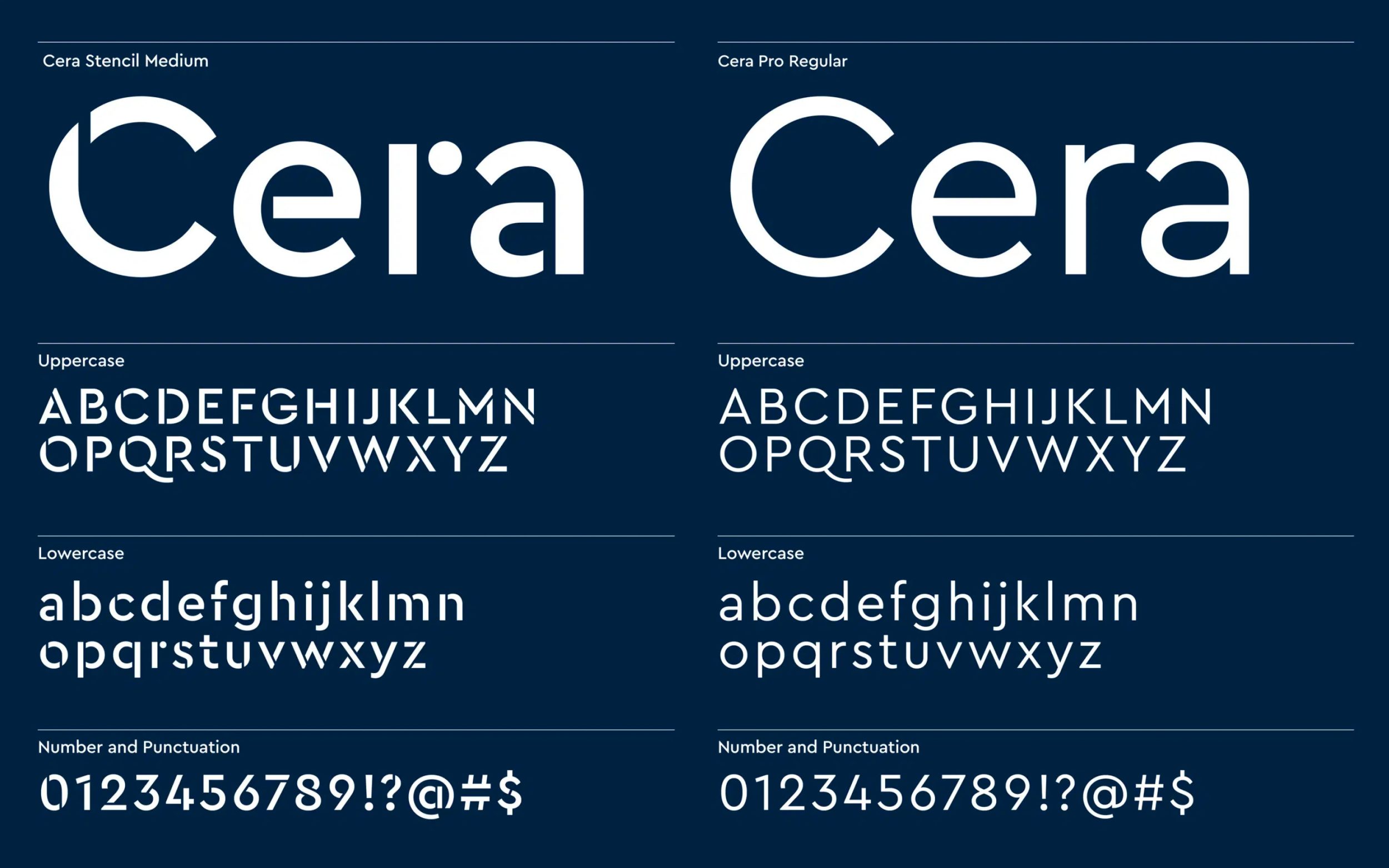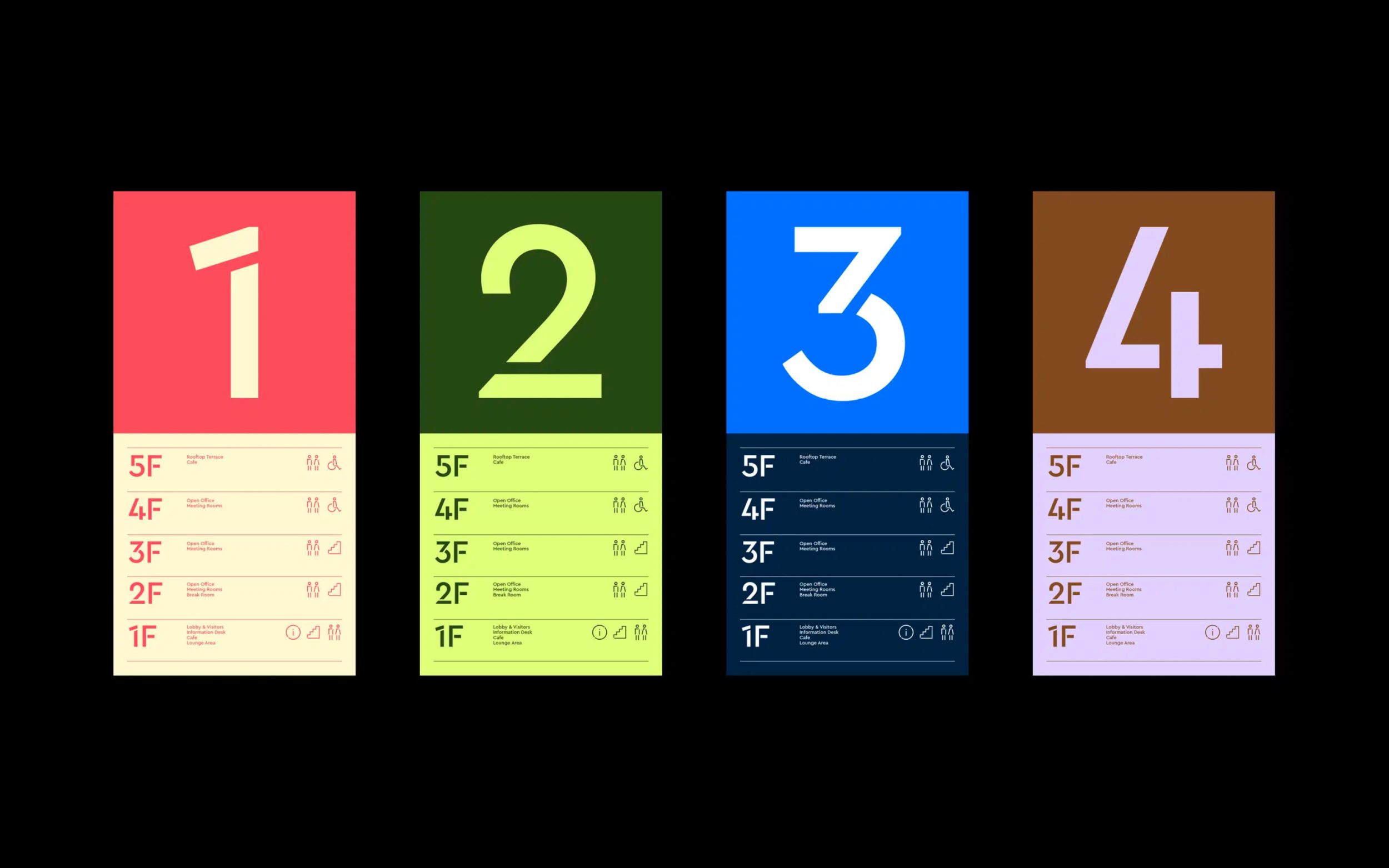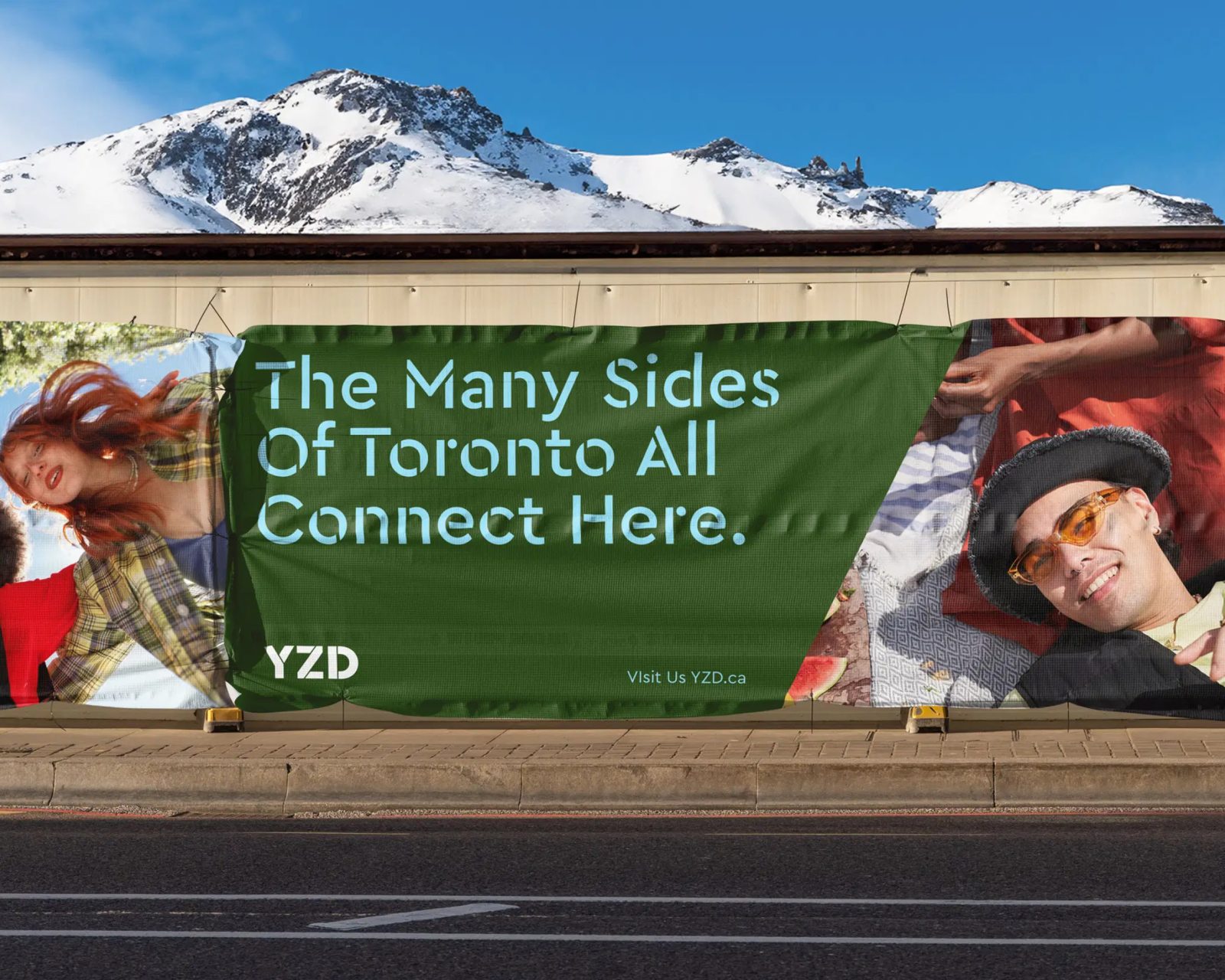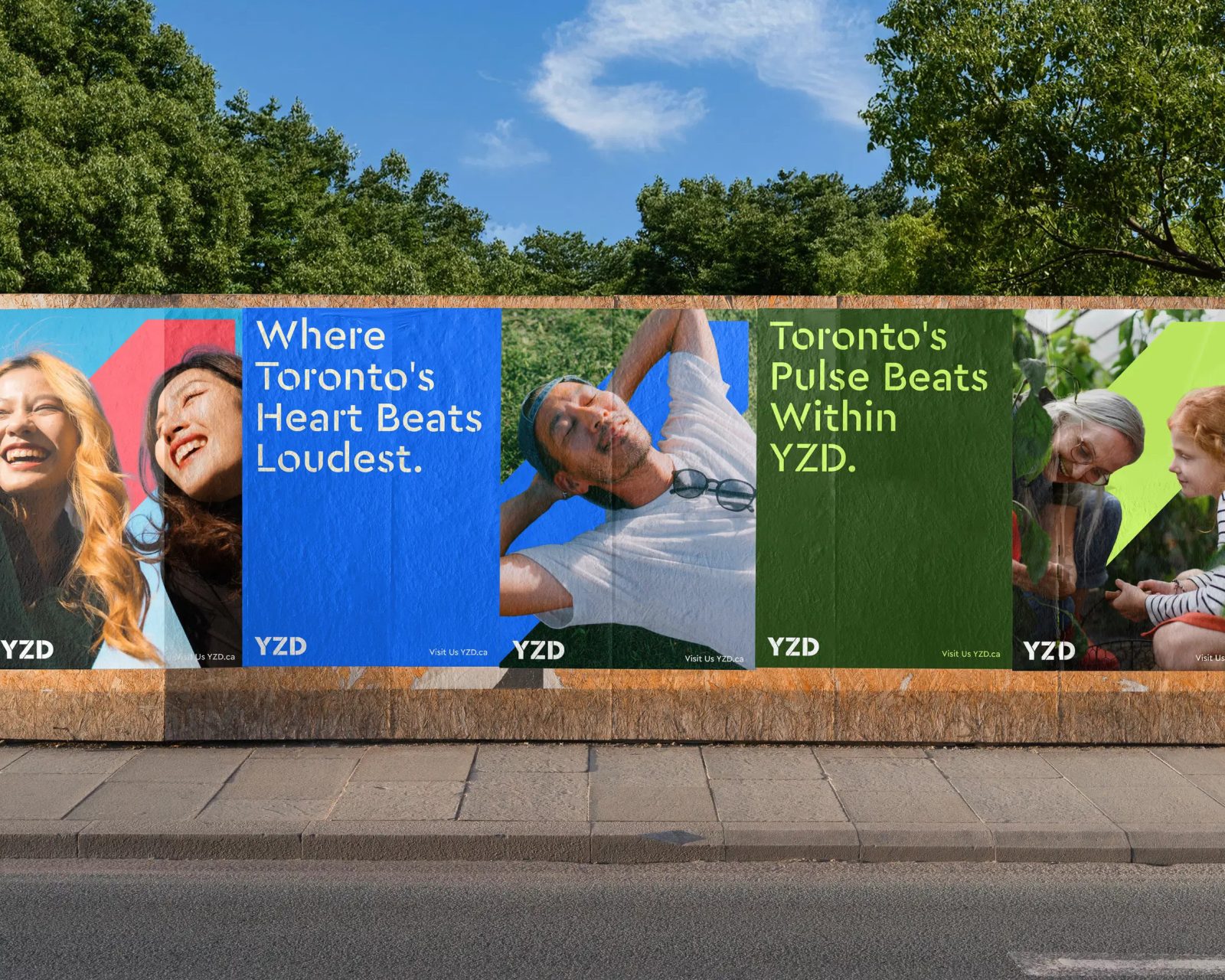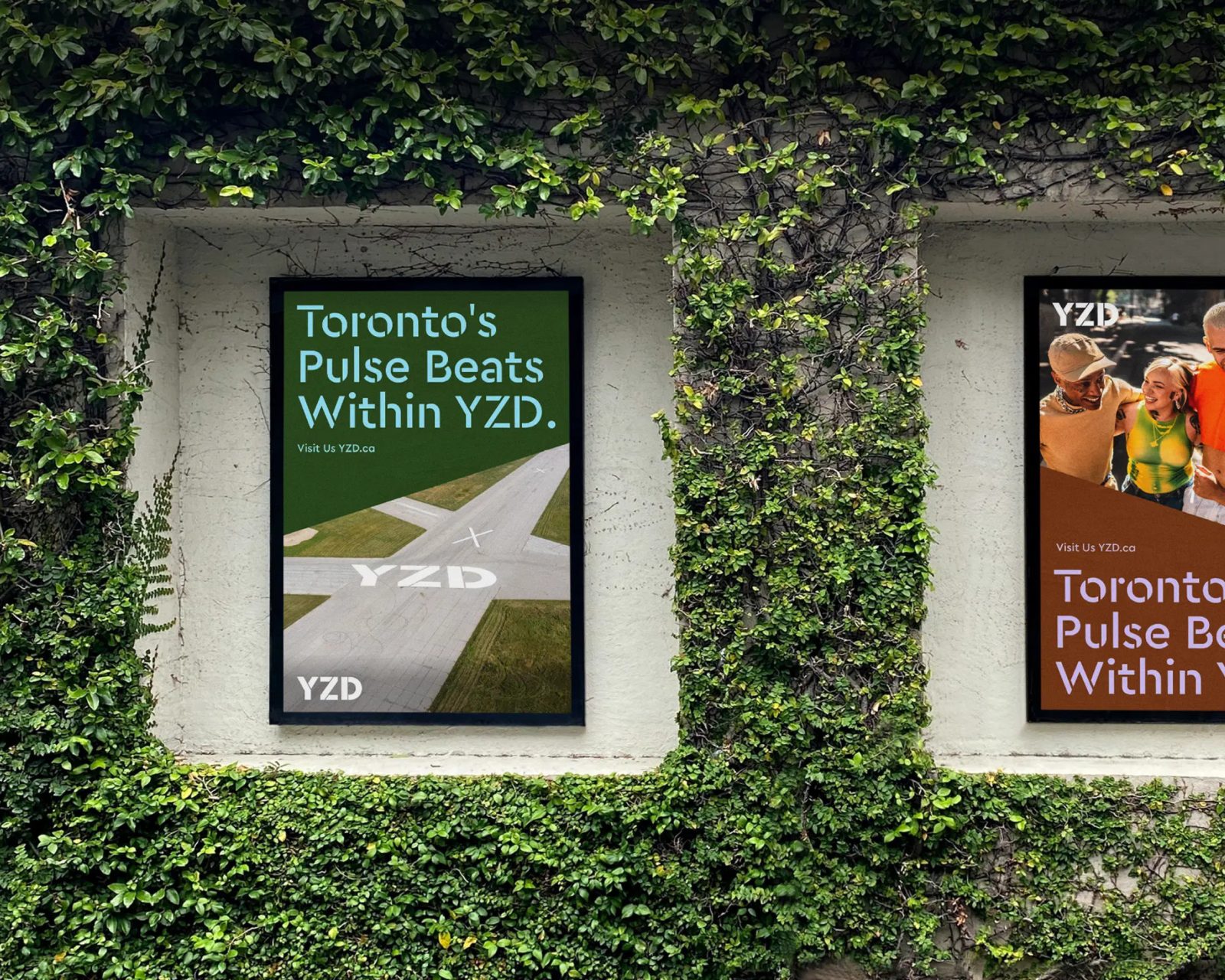
YZD Brand Identity von Pentagram
Für Torontos wegweisendes Stadtentwicklungsprojekt liefert die Cera Collection ein typografisches System, das das Flughafenerbe würdigt und gleichzeitig neue Stadtidentität schafft.
YZD zählt zu den ambitioniertesten Stadtentwicklungsprojekten Nordamerikas: Auf dem Gelände des ehemaligen Flughafens Downsview (Rufname: YZD) bei Toronto sollen über einen Zeitraum von drei Jahrzehnten sieben neue Stadtteile für 60.000 Bewohner entstehen. Pentagram wurde mit dem Branding dieses monumentalen Projekts beauftragt.
Das Branding sollte die Luftfahrtgeschichte des Areals aufgreifen, gleichzeitig aber auch den Wandel hin zum offenen Stadtbezirk thematisieren. Für die Wortmarke wurde daher die Schablonenschrift Cera Stencil gewählt. Pentagram schreibt dazu: „Die Display-Schriftart ist Cera Stencil, die auf Flughafenbeschilderung Bezug nimmt und gleichzeitig in radikal unterschiedlichen Kontexten klar lesbar ist – von monumentaler Geländebeschilderung über Leitsysteme bis hin zu digitalen Plattformen und Mieteranwendungen.“ (Übersetzt aus dem Englischen) Ein weiteres Detail ist der 54-Grad-Winkel des Z in der Wortmarke YZD, der die tatsächliche Geometrie der zentralen Landebahn widerspiegelt.
Für den Fließtext wurde die Cera Pro gewählt, aus der auch die Cera Stencil hervorgegangen ist: eine geometrisch schlichte, aber dennoch warme Serifenlose, die universell einsetzbar ist. Das Projekt zeigt, wie Superfamilien mit verschiedenen Display- und Textschriften, wie die Cera Collection, in der Praxis funktionieren. So wird ein konsistentes, aber abwechslungsreiches Branding in verschiedensten Größen und Formaten möglich.